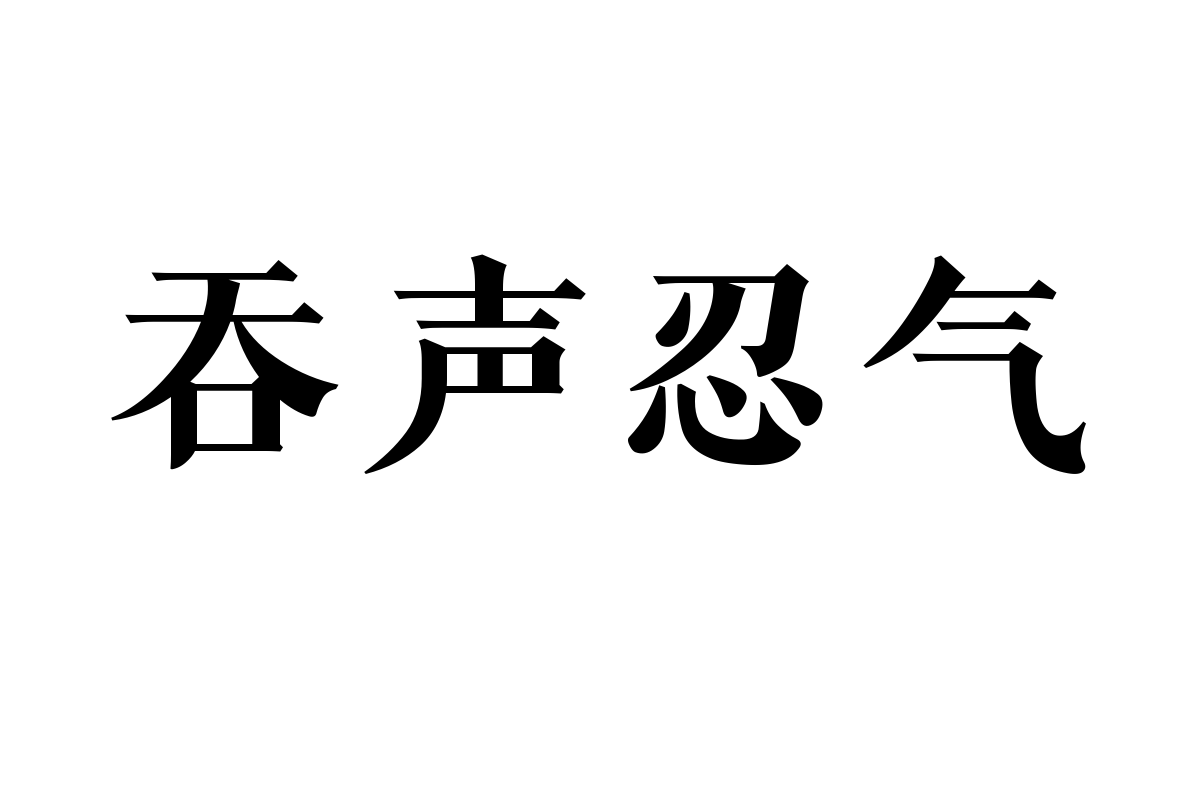
山海汲古明刻字体是一套具有中国传统风格的字体,它以中国古典文化为灵感来源,融合了古代汉字的书写技巧和美学理念。这套字体的特点如下:
1. 字形独特:山海汲古明刻字体的字形独特,线条流畅,既有古典韵味又不失现代感。每个字的笔画都经过精心设计,使得整个字体看起来既美观又富有艺术感。
2. 结构严谨:这套字体的结构严谨,每个字的结构和笔画都有严格的规定,使得整个字体看起来整齐划一,富有秩序感。
3. 风格古朴:山海汲古明刻字体的风格古朴,充满了浓厚的中国古典文化气息。它适合用于需要展现传统文化特色的场合,如书法、海报设计等。
4. 易于识别:由于这套字体的设计独特,因此很容易被人们识别出来。这使得它在各种场合下都能发挥出其独特的魅力。
总之,山海汲古明刻字体以其独特的字形、严谨的结构、古朴的风格和易于识别的特点,成为了一种非常受欢迎的中文字体。